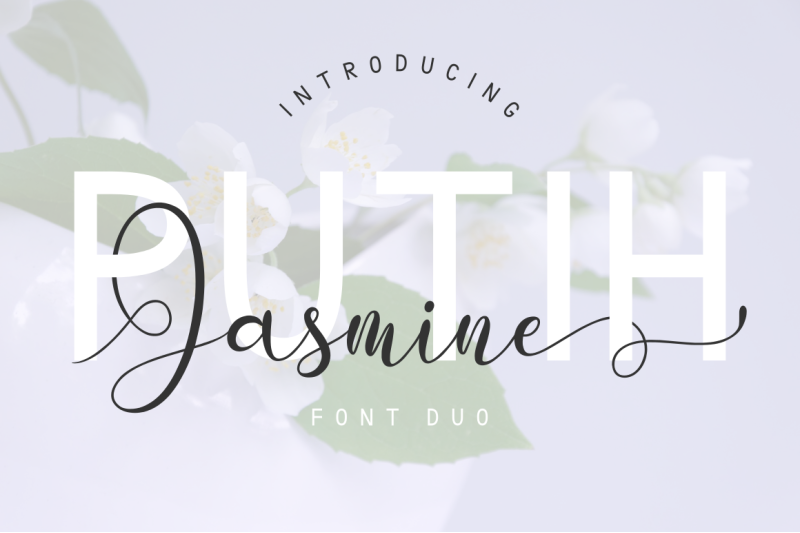
Putih Jasmine Font Duo – Fonte Grátis
Putih Jasmine Font Duo
A Putih Jasmine é uma nova série de fóntes criada pelo designer kammaqsum que agora está disponível para download na categoria Script Fonts da Alibaba Cloud. Esta fonte vem como um conjunto único e consistente de duas versões: uma script elegante e outra sans serif marcante. Fica claro que a font Putih Jasmine Font Duo é perfeitamente projetada para combinar com outras fóntes, mas também possui a força necessária para se destacar sozinha. Para designers amantes de um estilo delicado, a versão script oferece linhas delicadas e harmoniosas. Para aqueles que buscam uma solução mais moderna e robusta, a sans serif apresenta linhas finas e limpas. Esta fónte é perfeita para quem busca algo que se adapte bem ao estilo de escrita manuscrita, mas também oferece o poder da simplicidade dos fontes gerais. Com sua combinação única de elegância e forte estética, esta Putih Jasmine pode ser a fonte ideal para qualquer projeto visual que busque um equilíbrio entre sofisticação e força dinâmica.